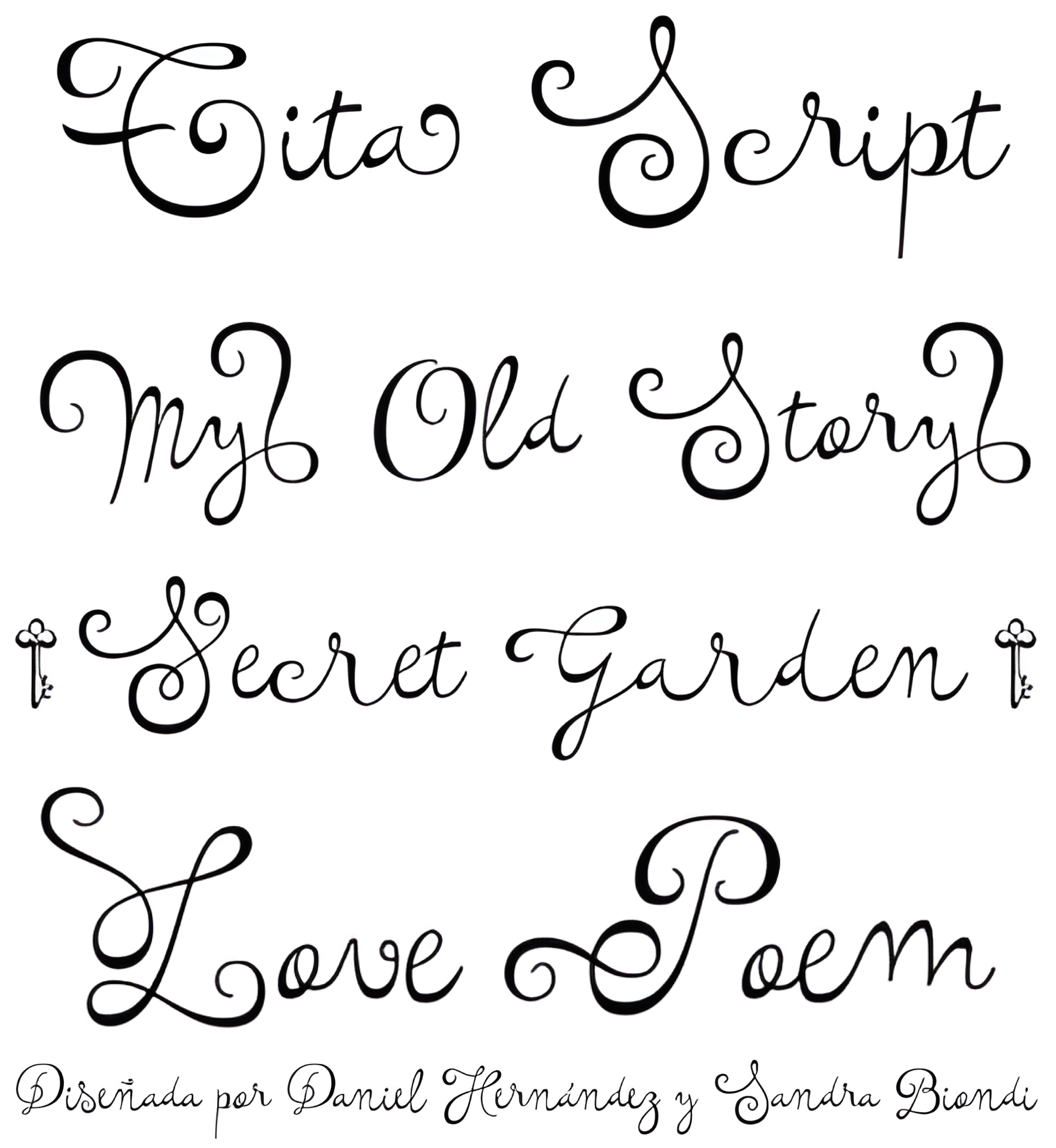
| Créditos | Daniel Hernández, Sandra Biondi |
| Descripción | Tita está dedicada a mi abuela Hebe, ingeniosa y arrabalera 1. La fuente está inspirada en la música de la Milonga 2 y el fileteado porteño 3. Me la imagino en el Moulin Rouge, chispeante, provocativa, cariñosa. Evoca a Tita Merello y a mi abuela cantando su música. Tita es argentina hasta la médula. Una fuente para gritar gol y dulce de leche 4 con pasión. Sus curvas tienen su origen en la caligrafía polirrítmica, que aprendí de mi mentora Silvia Cordero Vega. Tita es un tipo de letra con pedigrí que se basa en el hand lettering y en los trabajos caligráficos de Sandra Biondi. Digitalización de fuentes por Daniel Hernández. Editado por Javier Quintana / Programado por Manuel Corradine. 1. Una persona del arrabal (barrio obrero de la periferia de la ciudad de Buenos Aires) 2. Género musical originario de las zonas rioplatenses de Argentina y Uruguay 3. Letra decorativa y estilo artístico que se ve con frecuencia en Buenos Aires 4. Salsa de leche dulce |
| Clasificación | Títulos, Dingbats |